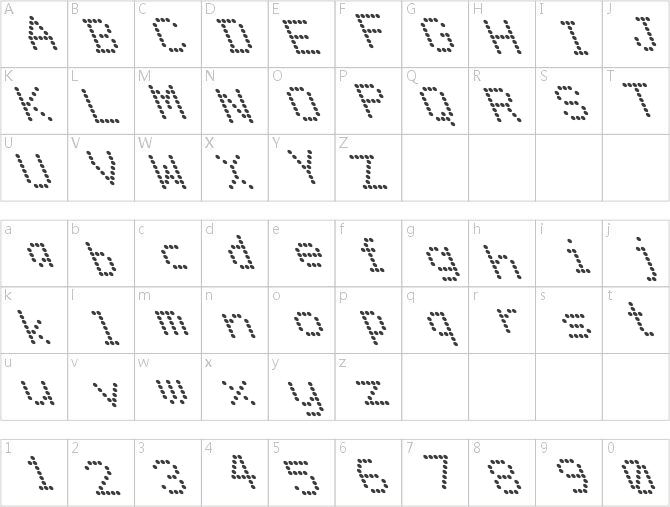
FZ DIGITAL 9 LEFTY 詳情頁
字體名稱: FZ DIGI
FZ DIGITAL 9 LEFTY
FZ DIGITAL 9 LEFTY字體字庫是一款讓人賞心悅目、百看不厭的英文字體,適合各類廣告和產品包裝設計應用,字體大小0.09MB,格式為ttf字體,上傳用戶是woslxn,作者/版權方為未知